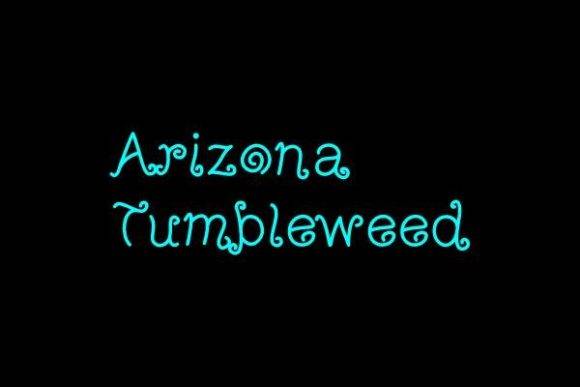
Fuente Arizona TumbleWeed para manualidades, logotipos y proyectos de impresión
Arizona TumbleWeed es una fuente manuscrita encantadora y original con curvas interesantes. Perfecta para productos modernos, diseños web, cartas o invitaciones, le da un toque único a cualquier proyecto.
- Estilo manuscrito
- Curvas interesantes
- Ideal para diseños de merchandising y web.
- Perfecto para cartas e invitaciones.
Aporta encanto y fantasía a tus proyectos con la fuente Arizona TumbleWeed .